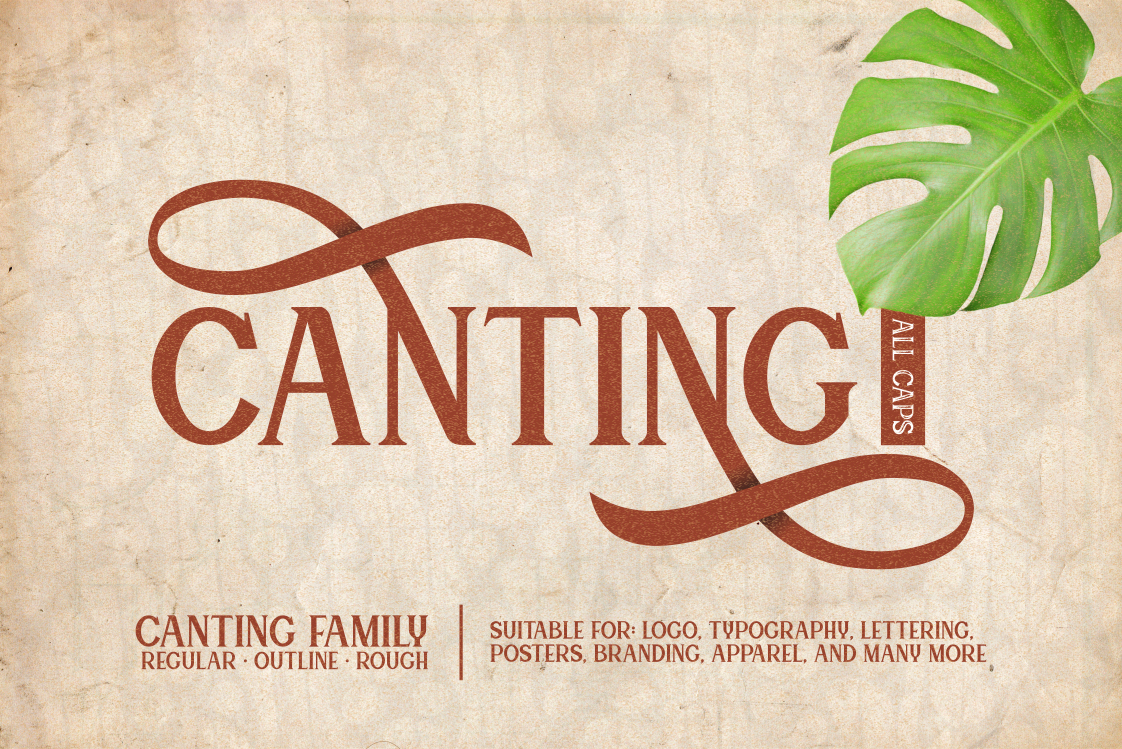
Canting é uma tipografia serifada que traz estilo vintage para o mundo moderno e minimalista. Ideal tanto para a criação de logotipos elegantes quanto para embalagens, letras de citações, design de posters e identidades de marcas, essa fonte especial oferece versões alternativas dos caracteres maiúsculos. Perfeita para designers que buscam uma fonte visualmente atrativa para seus projetos. Com sua rica característica da serigrafia na tipografia, Canting é a escolha perfeita para aqueles buscando um toque de sofisticação em suas criações.